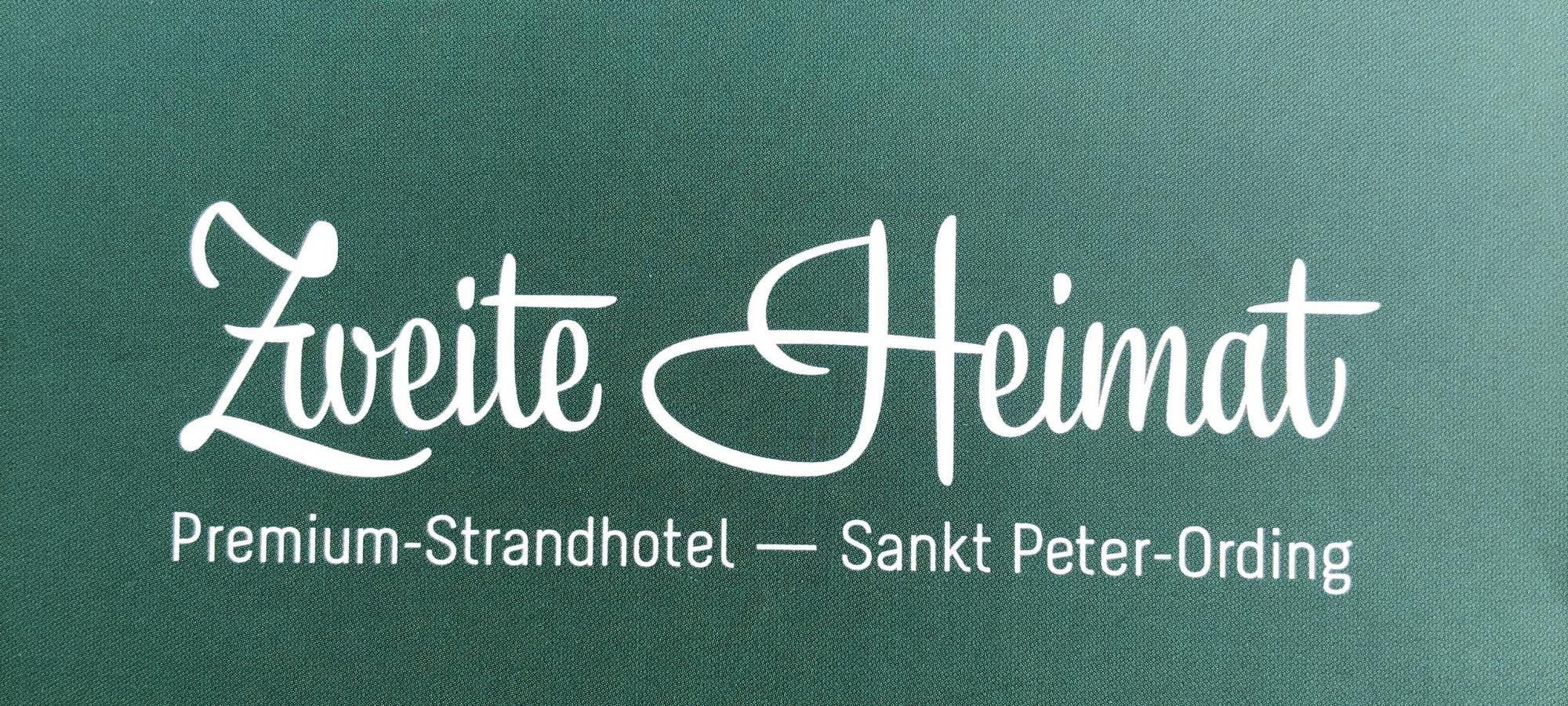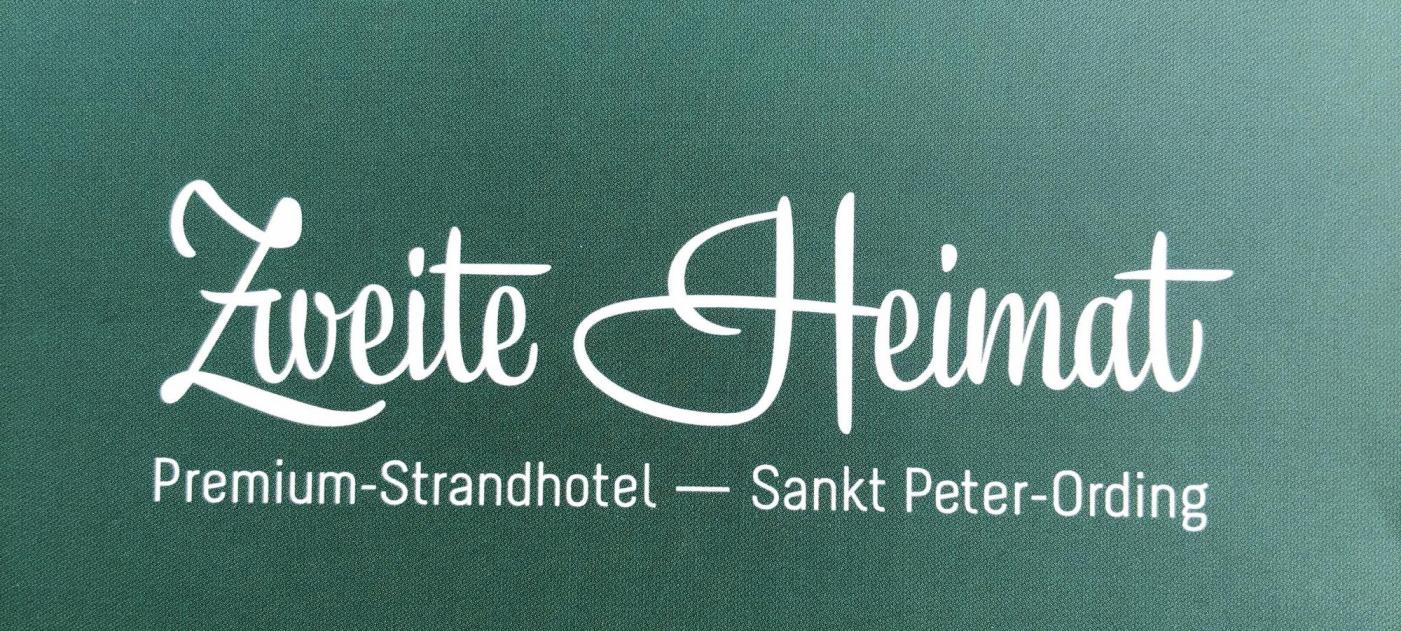
Schöne Script im alten Logo von »Zweite Heimat«
mir ist neulich die (alte) broschüre eines Hotels in st. peter-ording namens zweite heimat in die hände gefallen. dort wird – wie auch im alten logo – bei allen überschriften eine herrlich elegante (und trotzdem gefühlvolle aber nicht zu kitschige) schreibschrift verwendet, die mir verdammt bekannt vorkommt. whatthefont spuckt nichts vernünftiges aus und auf der website des hotels steht nur die neue broschüre zum download bereit. in selbiger haben sie leider leider – wie auch auf der gesamten website – stattdessen eine todlangweilige sans (texta book) verwendet. sehr traurig.
erkennt sie jemand von euch? hab richtig lust mir diese zuzulegen.